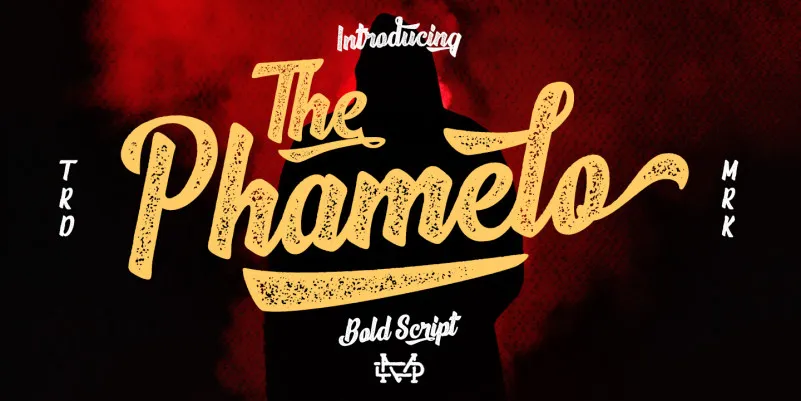
Phamelo Script Font – Download Grátis
A Phamelo Script é uma fonte tipográfica bold que oferece tanto versões limpas quanto rugosas, tornando-a ideal para qualquer projeto de design, seja ele em cartazes para eventos ou em designs digitais. Seu forte estilo script cria um efeito atraente e moderno, perfeitamente adaptado para textos longos como logomarcas, cabeçalhos e capa de livros. Com sua versão leve que exibe linhas grossas e seu lado mais rugoso, a Phamelo Script oferece uma variedade incrível em escolhas de visual. Ideal tanto para um ambiente sofisticado quanto para um design mais casual, esta fonte é certamente uma ótima opção para designers gráficos buscando algo especial e único.